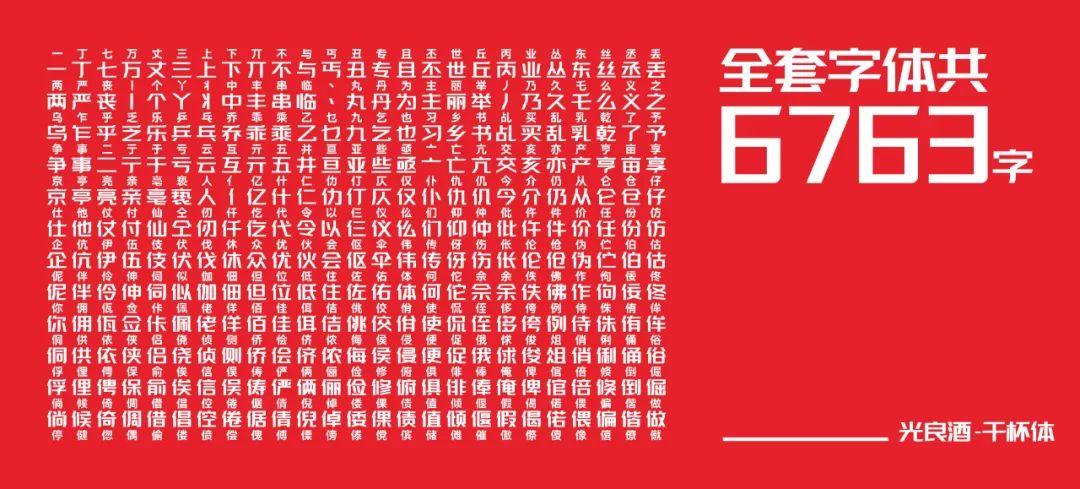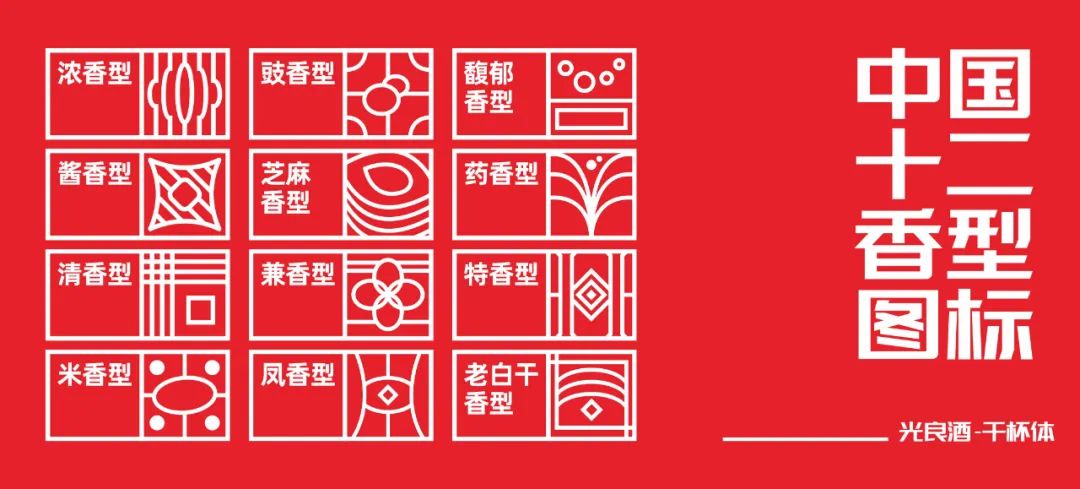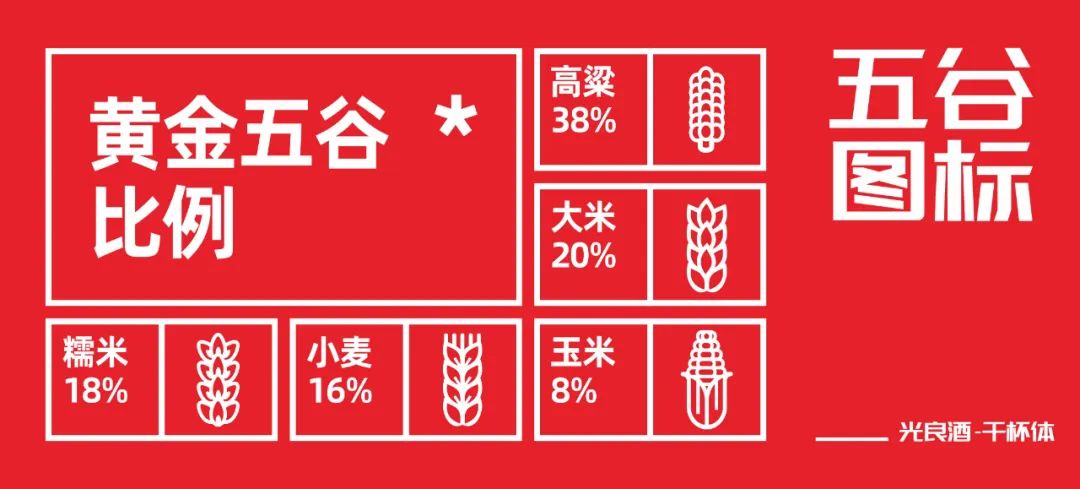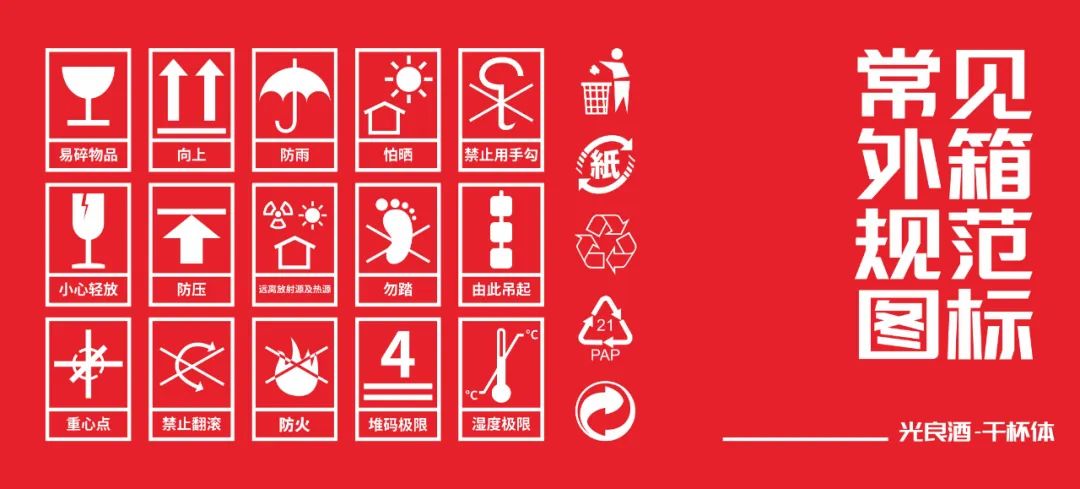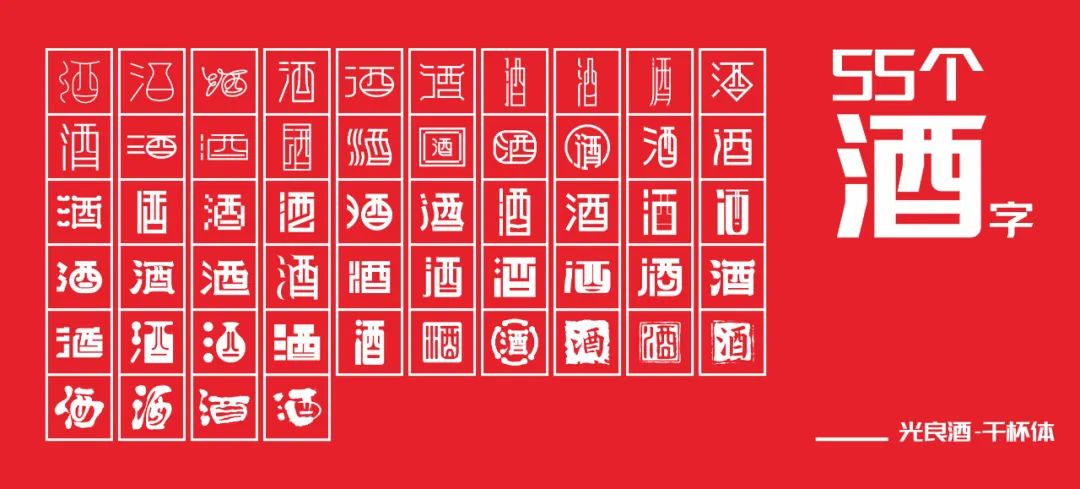
光良酒业花了26万设计了一套字库,免费可商用,这款字体结构工整、笔画清晰,兼顾美观与易读性,适用于标题、正文、海报、包装、LOGO 等多种场景。字形优雅稳定,风格百搭耐看,适配日常排版与创意设计,让文字呈现更舒适、更具质感。光良酒业花了26万设计了一套字库,免费可商用一笔一画,皆是细节,以均衡的比例、流畅的线条打造舒适视觉体验,字形端正大气,风格简约现代。无论是商业设计、品牌宣传还是日常排版,都能轻松驾驭,让文字更有格调与力量。光良酒业花了26万设计了一套字库,免费可商用字体下载。
我们花26万,干了一件"闲事"
26万,能做什么?
新春伊始,我们为所有白酒行业的同仁们准备了一份小小的礼物。
PART 01
天下苦"碰瓷式维权"久矣
耕耘行业数年,相信许多同仁都经历或了解过"碰瓷式维权"事件:
2022年3月,四川谷小酒商贸有限公司因在牛年生肖产品中使用"牛气冲天"字样,被"牛气冲天"商标持有方滨州市一品天下酒业有限公司指控侵权,并被处以283万元的天价罚单;
2021年底,四川数十家餐馆被上海万翠堂餐饮服务公司以上述餐饮店店招中所含"青花椒"商标侵权为由告上法庭。在该案一审中,被告之一温江五阿婆青花椒鱼火锅店被判决赔偿万翠堂公司经济损失3万元;
2013年起,随着江小白的热销,重庆市江津酒厂(集团)有限公司不断向重庆江小白酒业有限公司及关联公司提交的"江小白"系列商标提交商标异议和无效宣告申请,此后双方陷入了长达7年的商标争夺战;
作为一家初创企业,光良酒业和上述众多企业一样,遭遇过多次"碰瓷式维权":
对大部分品牌来说,以微信公众号为代表的自媒体平台已然成为被控"侵权"的高发阵地,而其中首当其冲的便是字体侵权。当因为无意间使用而被控"侵权"及索赔时,品牌方不得不删除辛苦产出的内容,或者向索赔方进行高额的赔偿。
当此类事件频繁发生时,往往会给企业造成非常大的困扰,甚至不得不求助于专业的维权机构,耗费较多的时间和精力。
PART 02
因为我们都淋过雨  所以想为大家撑一把伞
去年年初,江小白酒业创始人陶石泉先生在创业10年之际撰文《10年,活下来已经很不容易》,引发了行业内外诸多创业者的广泛共鸣。
创业不易,守业更甚。光良酒业诞生于行业调整期内,发展初期便面临着疫情的爆发和持续;首创的数据瓶产品上市半年后,随之出现大量山寨及仿品乱市;更有日常传播推广中面临的各类"维权"……仅此四年,步履维艰。
作为一家致力于打造国民自用酒的初创企业,我们深知成长过程中的艰辛和不易,更知道当我们想在这个行业做一些微小的创新和美好的传达时,所需要付出怎样的时间和心血。
路漫漫而修远,总要有人做出改变。
PART 03
走在探索路上
从2019年初正式上市以来,光良酒被业内人士称为"革新者"、"破局者",一方面是由于洞察到行业沉疴后,开创性地打造出"数据瓶"系列产品,凭借用酒体比例命名的坦诚直白,让市场和消费者认可并信赖"有态度的光瓶良心酒";
更因为,成长中的光良,从未停止过探索的步伐。我们联动先进的互联网平台,探索这个时代的消费者需要怎样一瓶自用酒;也勇敢地向前一步,探索新光瓶世界的诸多可能性;我们探索海拔4千米雪山清晨的第一抹朝阳;也探索飞天仙女和宇航员指尖跨越千年触碰的绝妙火花……我们在传统中诞生,正行走在未来的大道上。
这一次,我们回归自身,历时9个月,花费26万,为自己,也为整个白酒行业的同仁们,探索一条无忧之路。
PART 04
寒冬不寒 光良有光
去年3月,我们决定做一款自己的字体,便于自己以及整个白酒行业的所有同仁突破桎梏,放心使用。
我们联系了全网第一的资深字体设计师刘兵克及其创办的"字体江湖"团队,用了大半年时间,研发了品牌字体【光良酒-干杯体】,并决定免费开放给公众使用(包括商业用途)。
"我从事设计工作近20年,从未遇到过这样的客户。相信在这个寒冷的冬季,光良酒也将为白酒行业的同仁们带来许多温暖。"
这套字体总共有6763个常用字,此外,考虑到大家在实际使用中的多种情况,我们还设计了55个不同的"酒"字标识,以及原料、香型、货运相关的数十个标识,希望能为酒业同仁们的传播使用提供方便。